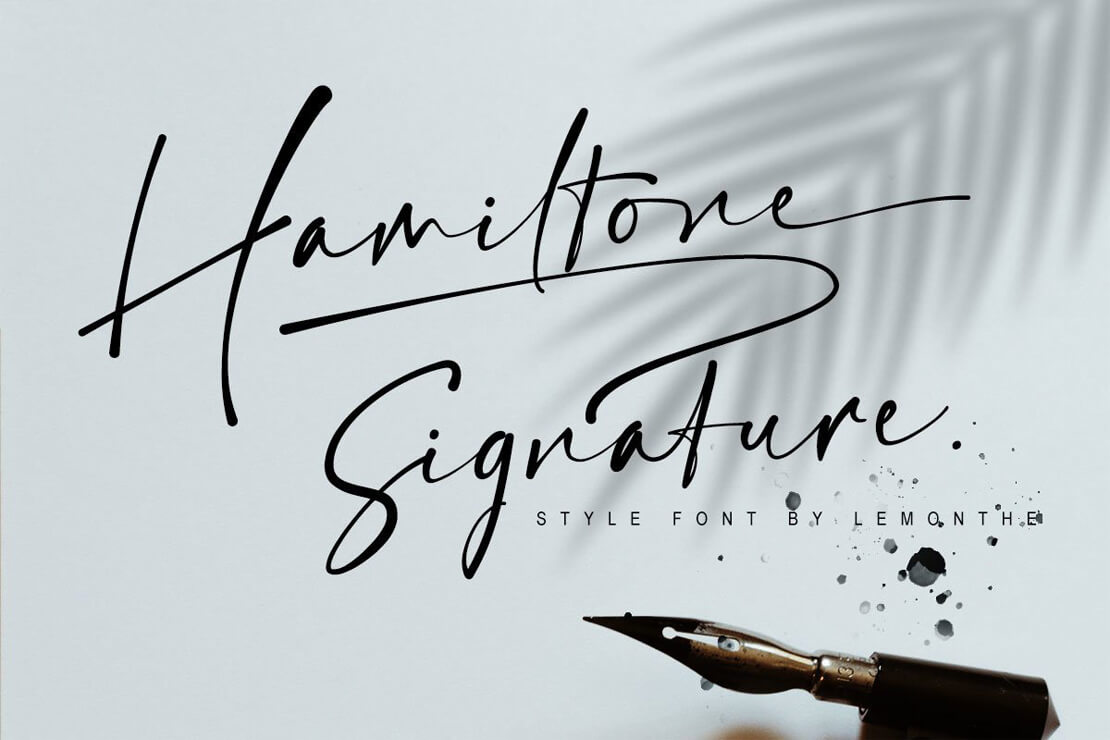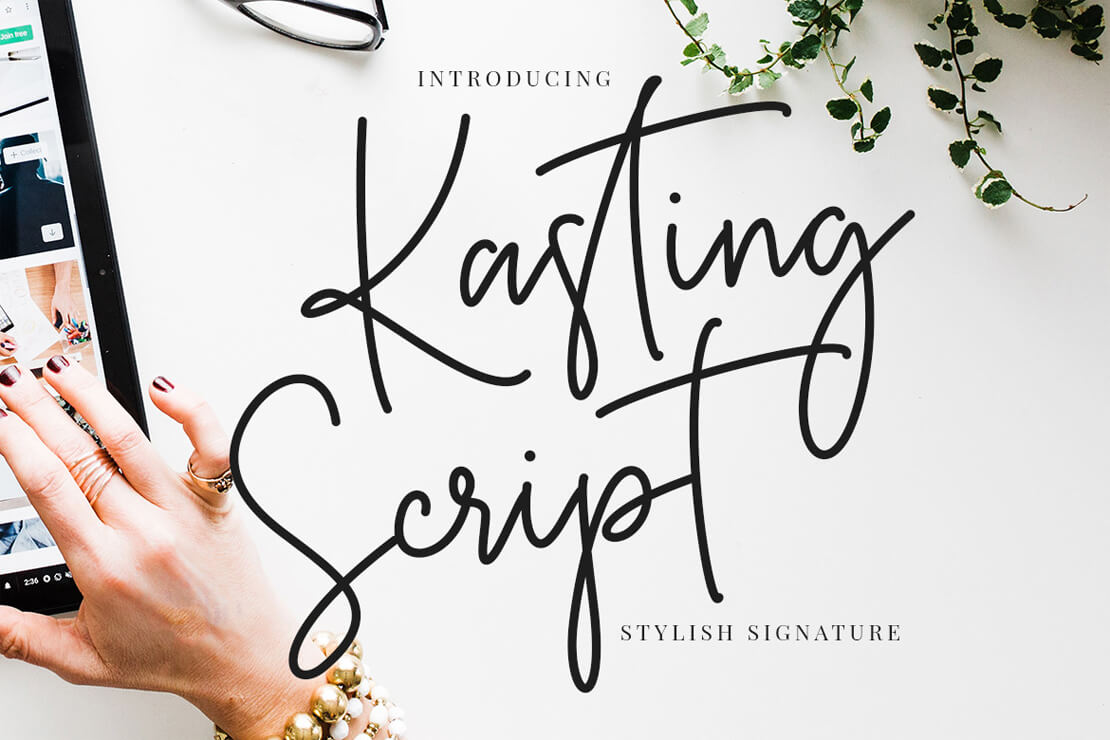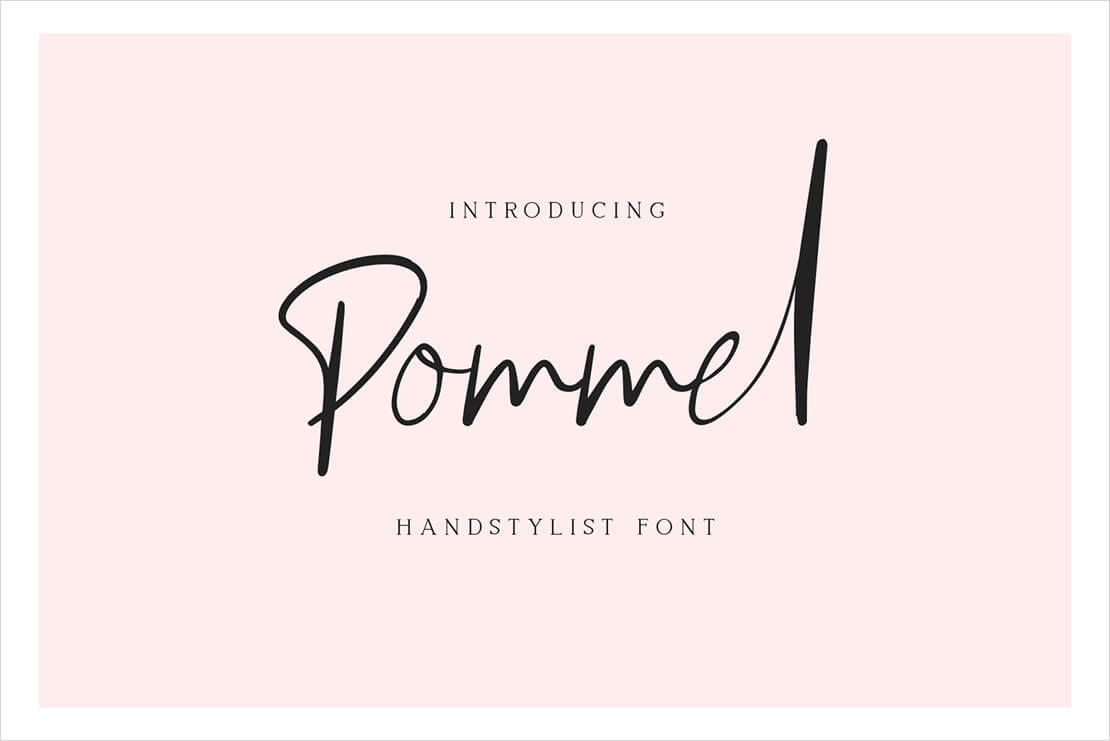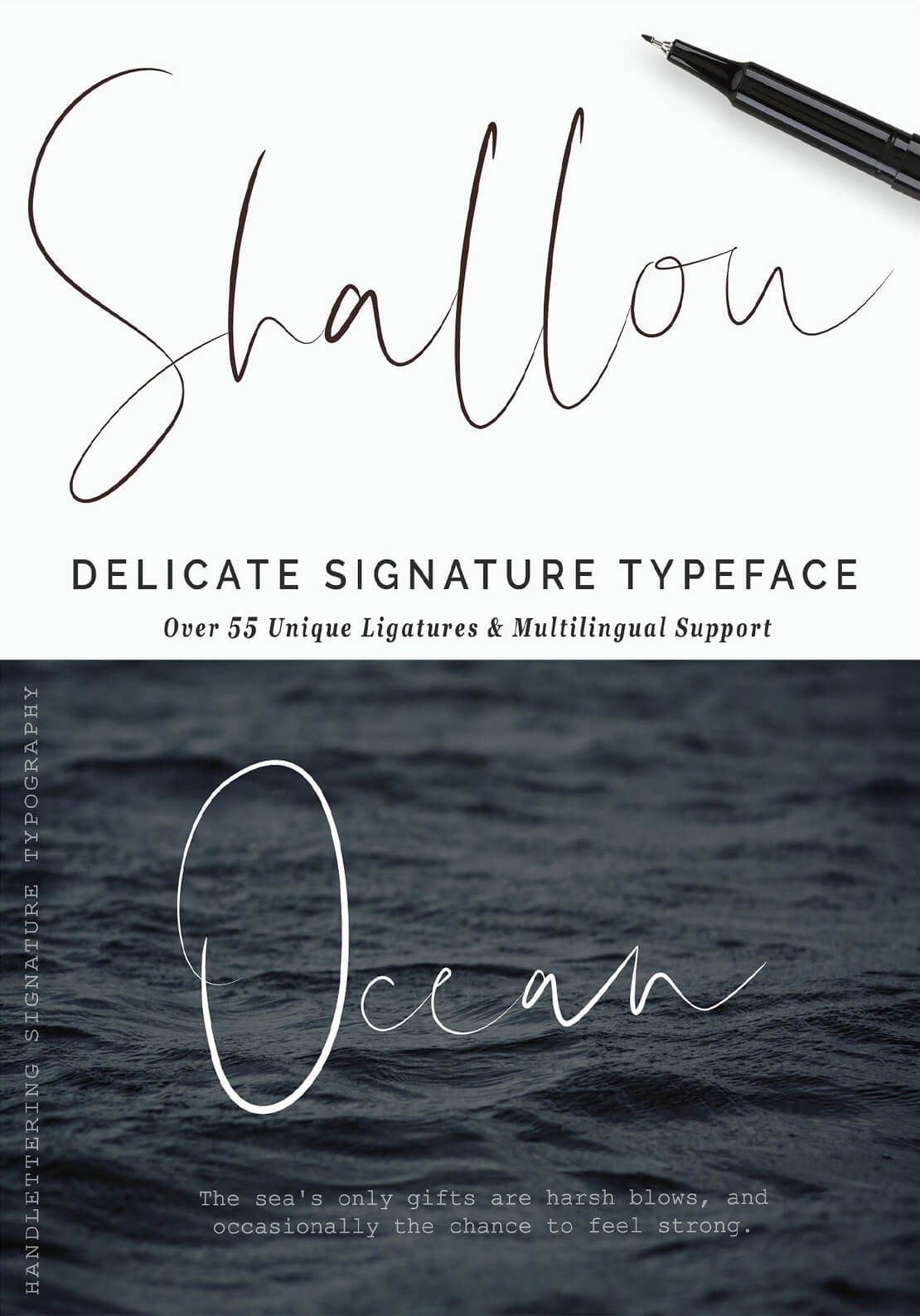
Signature-Fonts zum Downloaden
Signature Fonts sind beliebt. Schriftarten, die aussehen wie Unterschriften oder expressiv von Hand geschrieben herüberkommen, haben vielfältige Einsatzmöglichkeiten. Hier kommen einige Signature Fonts, die es aktuell kostenlos zum Downloaden gibt.
Signature Fonts: Eine persönliche Note im Design
Schriftarten spielen eine wichtige Rolle im Designprozess und können maßgeblich zum Erscheinungsbild eines Projekts beitragen. Eine besondere Schriftart kann dabei helfen, eine individuelle Note zu verleihen und das Design von der Masse abzuheben. Eine spezielle Gruppe von Schriftarten sind die sogenannten „Signatur-Schriftarten“, die einen auffälligen, handschriftlichen Charakter haben und oft wie echte Unterschriften aussehen.
Signatur-Schriftarten sind geeignet, um ein persönliches Flair in das Design zu bringen. Der Fokus liegt hierbei oft weniger auf der Lesbarkeit als vielmehr auf dem künstlerischen Ausdruck und der Ausstrahlung der Schrift. Type-Designerinnen und Type-Designer von Signature Fonts möchten oft eine stilvolle und ausdrucksstarke Schriftart schaffen, die eine individuelle Note vermittelt und sich gut mit anderen Schriftarten kombinieren lässt.
Hier kommt eine Auswahl mit Signature Fonts, die sich kostenlos herunterladen lassen.
Creattion – Free Signature Script Font
Die Schriftart „Creattion“ von Glyphstyle ist ein Beispiel für die Eleganz und den Charakter, den man mit Signature-Fonts verbindet. Die Schrift wurde tatsächlich mit Tinte geschrieben und vermittelt dadurch einen sehr persönlichen und individuellen Touch. Die Schriftart eignet sich unter anderem für Logos, Geschäftsbriefe oder Einladungen.
Antariksa Signature Font
»Antariksa« ist ein kalligraphischer Signature Font. Die Schrift ist in zwei Varianten verfügbar, als Regular und Slant. Der Free Font kann für private Zwecke heruntergeladen und genutzt werden. Die kostenpflichtige erweiterte Version kann über die FontBundles-Plattform bezogen werden.
Der Font wurde von Sronstudio entworfen und ist unter anderem für persönliche Projekte wie Einladungskarten, Grußkarten oder persönliche Briefe geeignet. Die geschwungenen Buchstaben vermitteln ein elegantes und ausdrucksstarkes Schriftbild, das den persönlichen Charakter der Botschaft unterstreicht. Darüber hinaus kann der Font auch für professionelle Zwecke wie Logo-Designs oder Visitenkarten genutzt werden.
Mit der Slant-Version können zudem zusätzliche Akzente gesetzt werden, die dem Text eine dynamische und individuelle Note verleihen.
Bastliga | Realistic Signature Font
Der Signature Font „Bastliga“ ist eine Schriftart, die den Eindruck erweckt, als sei sie mit einer Feder oder einem Pinsel geschrieben worden. Sie ist zudem kostenlos und kann für die private Nutzung heruntergeladen werden. Das Schriftbild ist charakteristisch und elegant, was sie zu einer ansprechenden Wahl für den Einsatz in verschiedenen Projekten macht.
Gosseliena Handwritten Signature Font
Der Signature Font »Gosseliena« ist eine ansprechende Wahl für alle, die eine Schrift suchen, die Eleganz und Leichtigkeit ausstrahlt. Der kalligrafische Stil der Buchstaben verleiht dem Font einen besonderen Flair und eignet sich unter anderem für Hochzeitseinladungen, Logos und mehr.
BrittanyAgustina Monoline Signature Free Font
BrittanyAgustina ist ein eleganter Signature Font, der den Eindruck vermittelt, als wäre er von Hand geschrieben worden. Er wurde von Mononline gestaltet und ist mit Opentype-Features ausgestattet, die es einem ermöglichen, ohne Absetzen zu schreiben. Die Schriftart ist beispielsweise geeignet für den Einsatz in Hochzeitseinladungen, Logos und anderen kreativen Projekten, bei denen eine persönliche Note erwünscht ist.
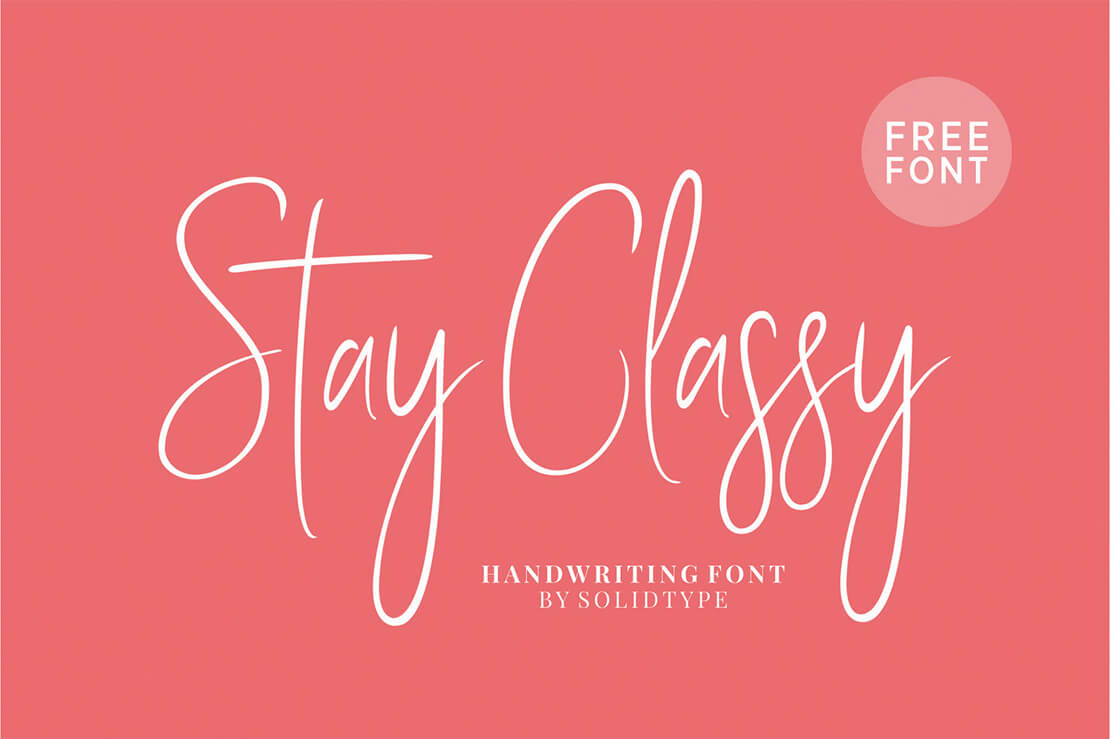
Für elegante und klassische Designs wurde »Stay Classy« entwickelt. Der kostenlose Signature Font vom Typeface-Design-Studio Solid Type darf zudem auch für kommerzielle Projekte verwendet werden.
Mightam
»Mightam« wurde für die Verwendung in kreativen Projekten entwickelt. In der kostenlosen Version dieses Signature Fonts sind die Schnitte »Regular« und »Brush« enthalten.
Tuesday Night Signature Script